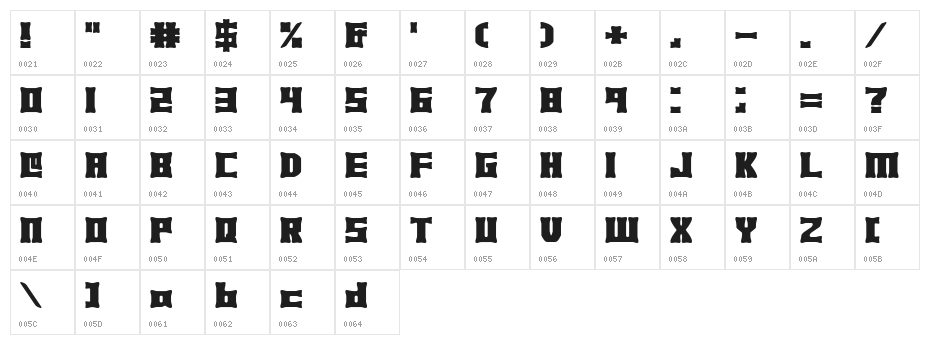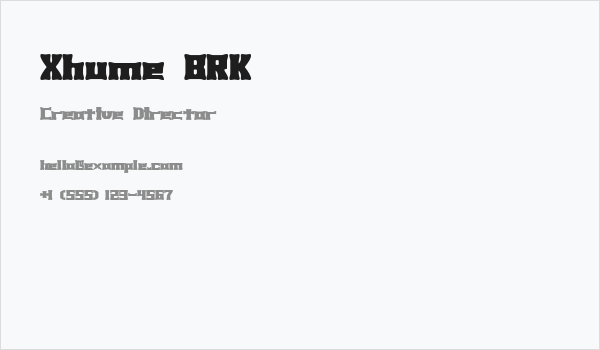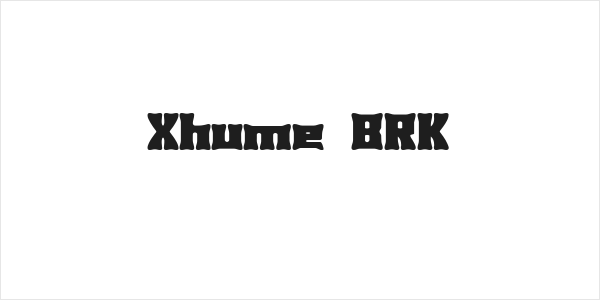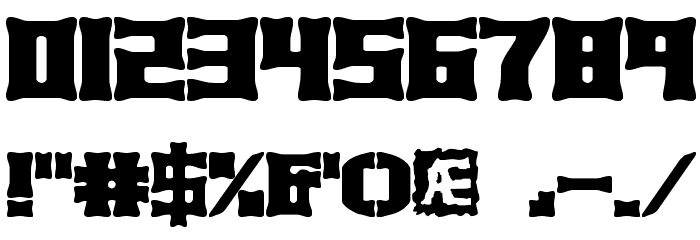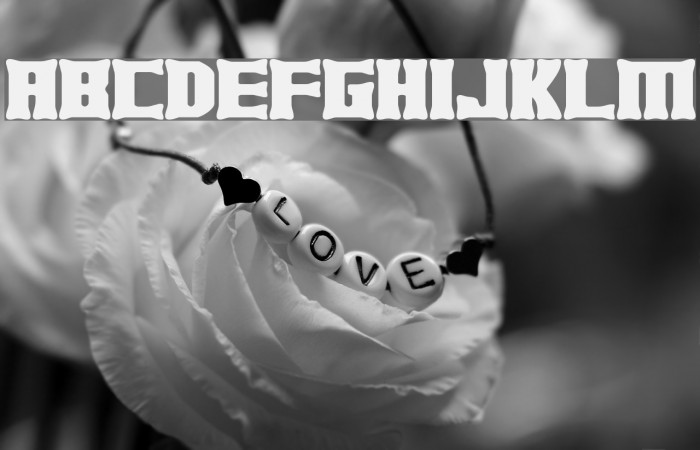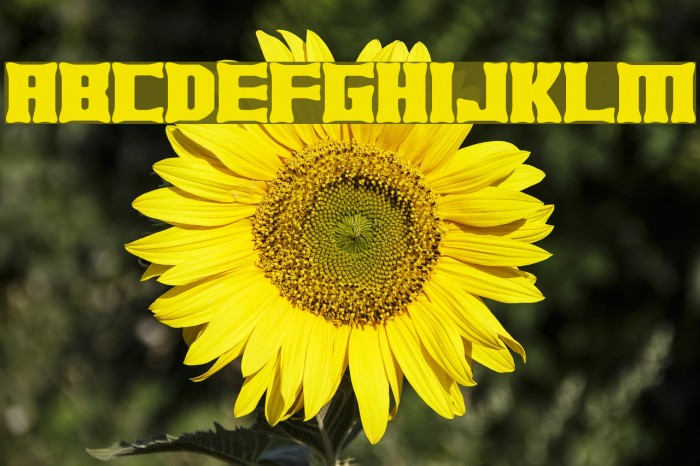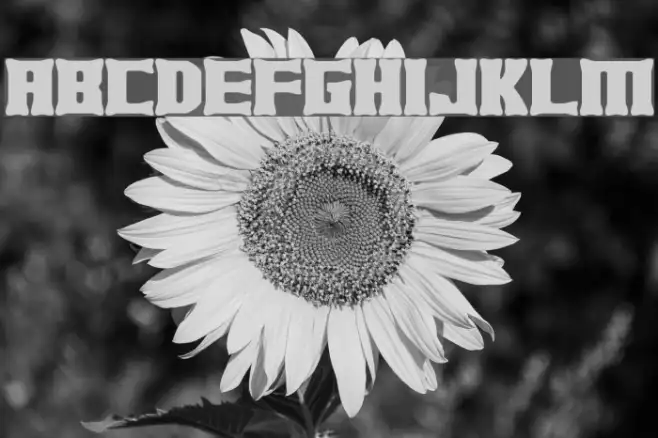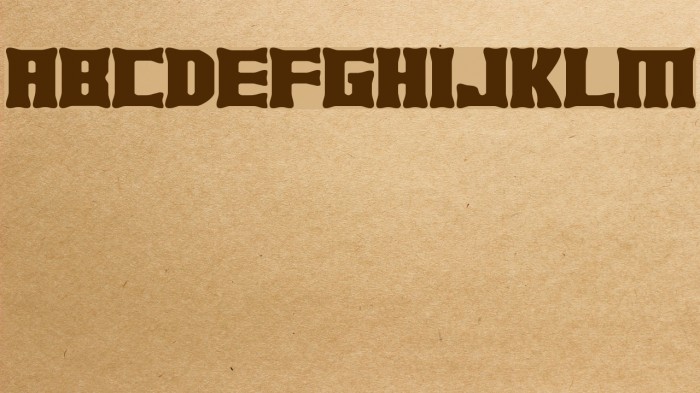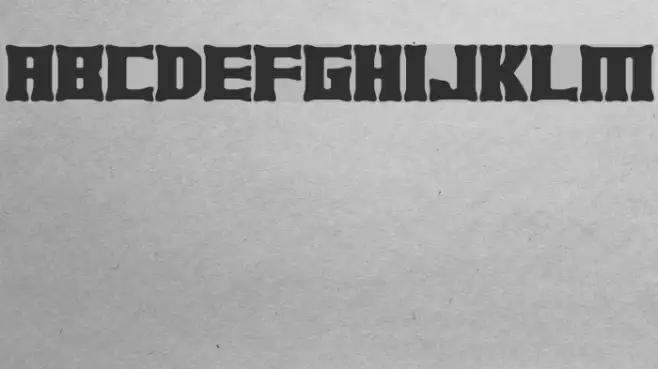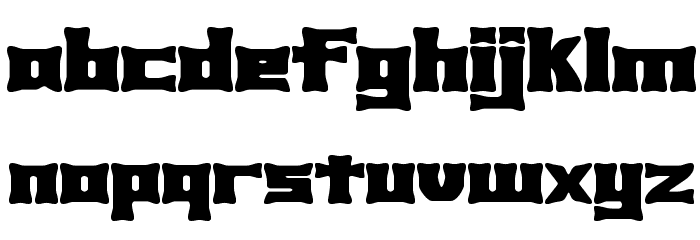
Xhume BRK Font
✎ Futuristic
| Vorgeschlagene Projekte | Ideal for posters, album covers, branding projects, and any design requiring a bold, rustic aesthetic. |